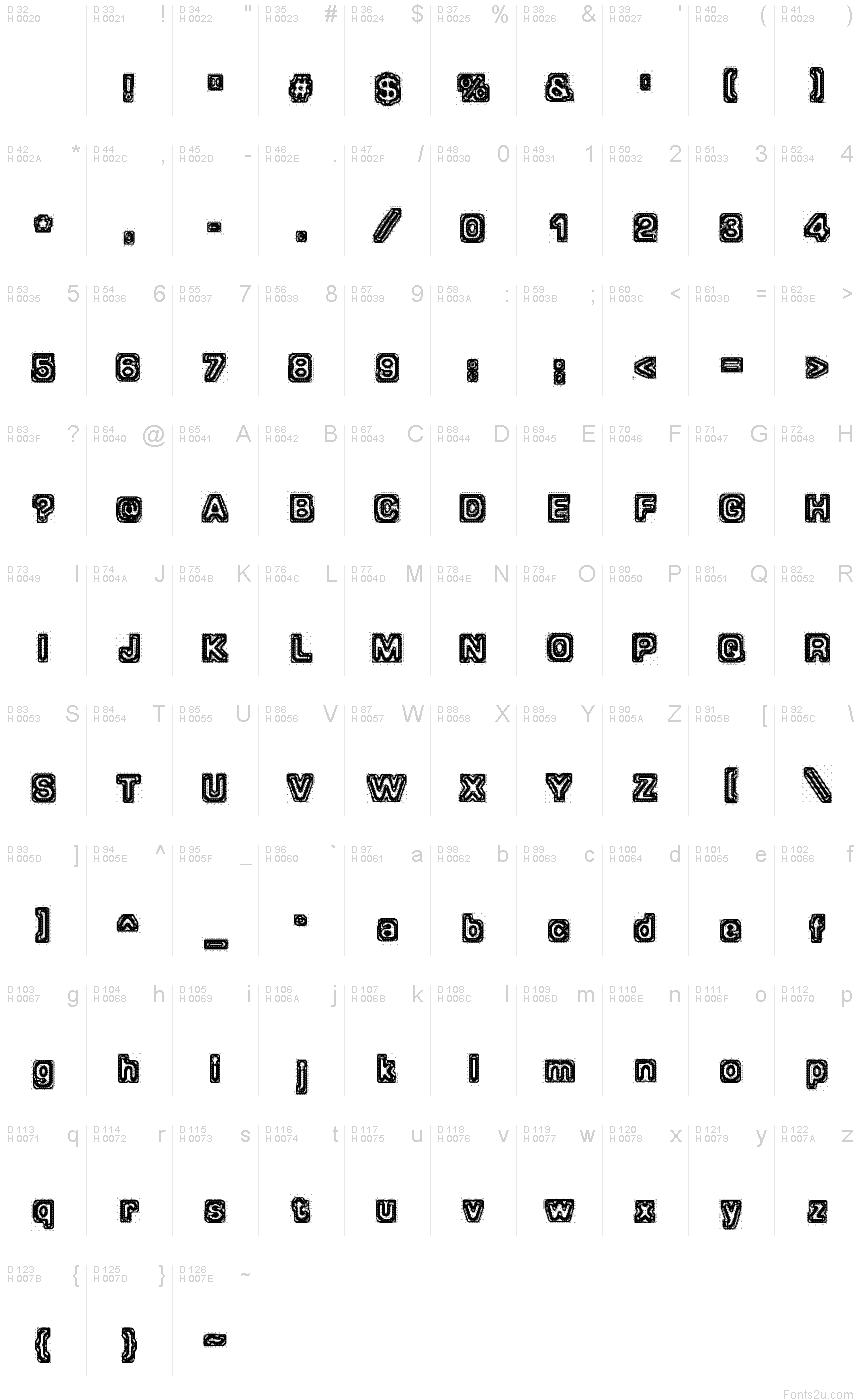
خط Brain-scan من تصميم Mr. FISK هو خط عرض (display) مجاني ذو طابع مشوه. تبدو كل حرف وكأنه خرج للتو من شاشة مشوشة، بأشكال مستديرة ضخمة محاطة بهالة ضبابية من النقاط والبقع، كما لو أن الحبر يهتز. تمنح هذه الخامة شعوراً بالخشونة والكهرباء في آن واحد، مما يضفي على العناوين طاقة خيال علمي مشوهة لا يمكن تجاهلها عند استخدامها بأحجام كبيرة.
يبرز هذا الخط المجاني بشكل مثالي في ملصقات أفلام الرعب أو السايبربانك، وأغلفة الألبومات ذات التأثيرات الرقمية (glitch)، وعناوين الألعاب المستقلة، ومنشورات فعاليات الخيال العلمي، والتصاميم الشبكية التجريبية. استخدم Brain-scan للعناوين القصيرة والقوية، ونسقه مع خط sans-serif نظيف ومحايد للنص الأساسي؛ فهذا يحافظ على وضوح القراءة وسط الفوضى، ويسمح لشخصية الخط المشوهة بالبروز بقوة وغرابة.